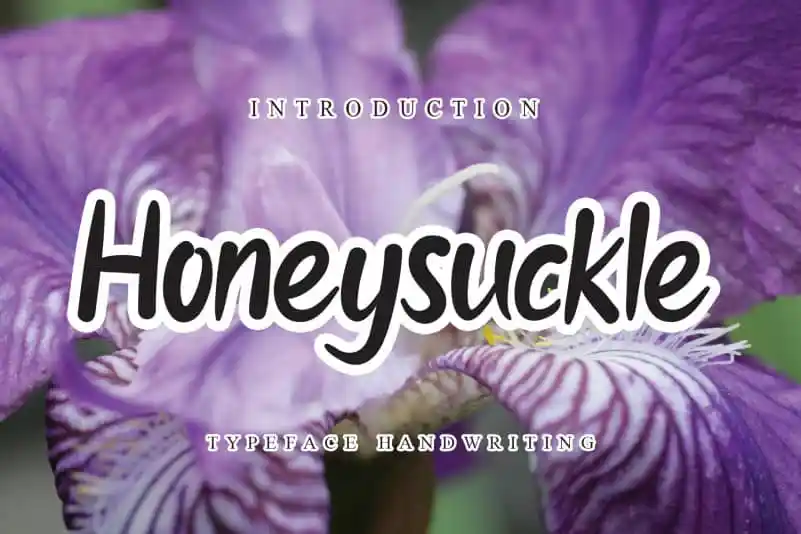
Honeysuckle Flower Script Font – Download Grátis
A fonte “Honeysuckle Flower Script Font” é uma opção simples e natural para aqueles que desejam adicionar personalidade à suas criações digitais. Embora simples, ela possui um charme único que emerge de sua natureza quase autêntica, inspirada na escrita a mão casca dourada. Casual e perfeita para qualquer aplicação gráfica, seja em cartazes, websites ou design editorial, esta fonte vai se destacar por seu apelo natural e elegante. Desenvolvida pelo designer andikastudio, ela é uma escolha ótima para quem busca um estilo que evoca sentimentos de tranquilidade e harmonia. Suas curvas delicadas e traços naturais combinam perfeitamente com textos em formato script, criando um resultado profissional sem perder a essência da escrita manual. Se você está procurando por uma fonte que se destaca pela sua simplicidade e beleza natural, “Honeysuckle Flower Script Font” é uma escolha inteligente para incorporar à sua coleção. Este design único traz um toque especial às criações digitais, permitindo que você personalize seus trabalhos de forma única e encantadora.